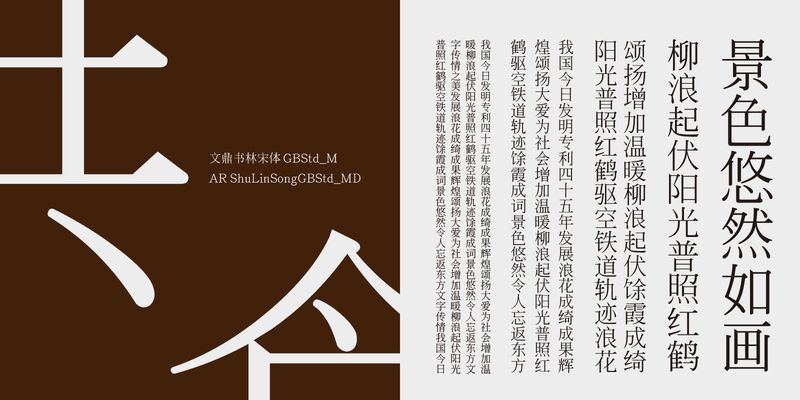
O design da fonte é baseado na AR Song: a estrutura é tradicional, o interior é condensado e a gravidade é maior. O design do chinês tradicional e simplificado é integrado para manter a consistência. A AR ShuLinSong foi atualizada em junho de 2018 para incluir glifos latinos do conjunto ISO 8859-1(00A1~00FF) e símbolos monetários usados com frequência.